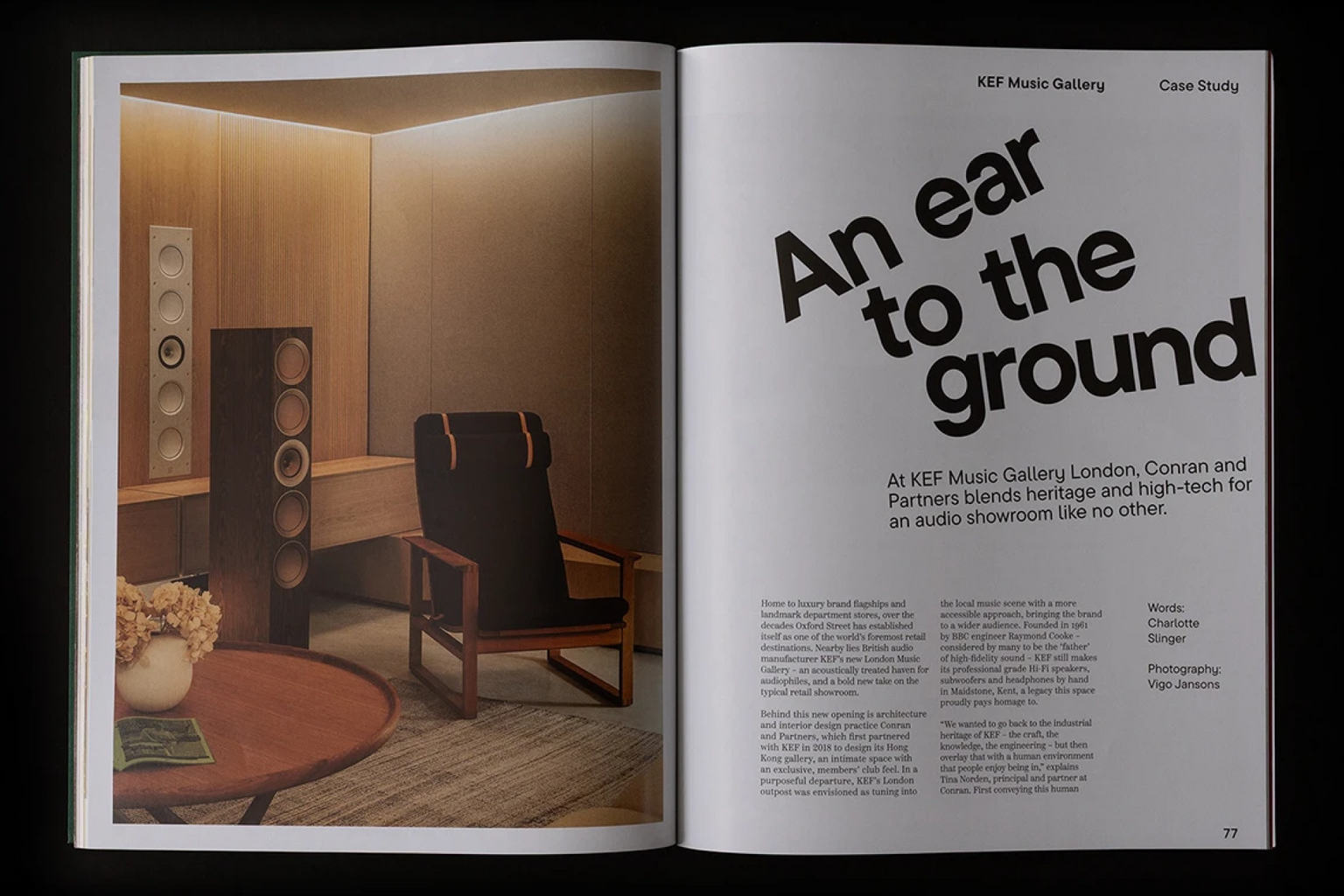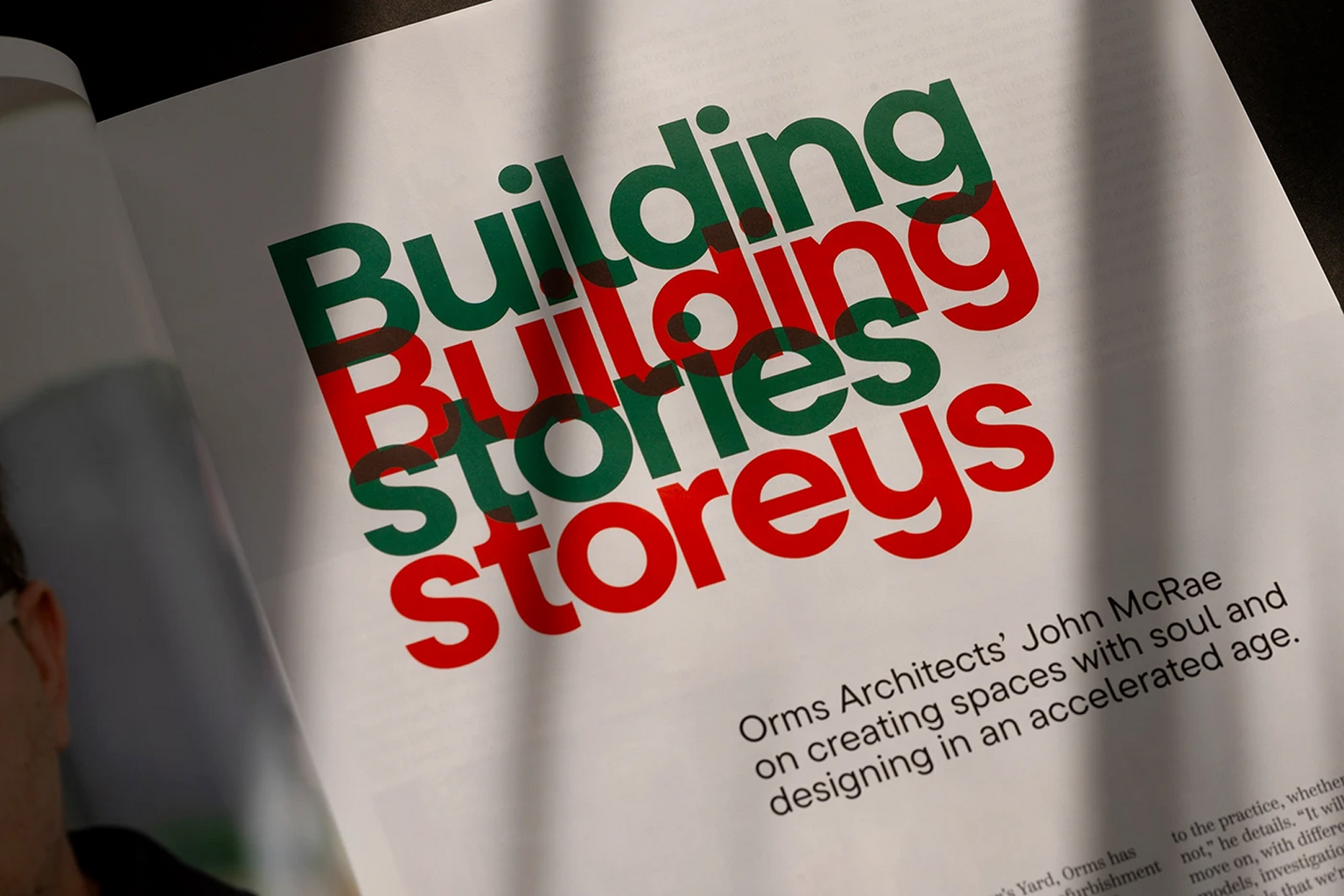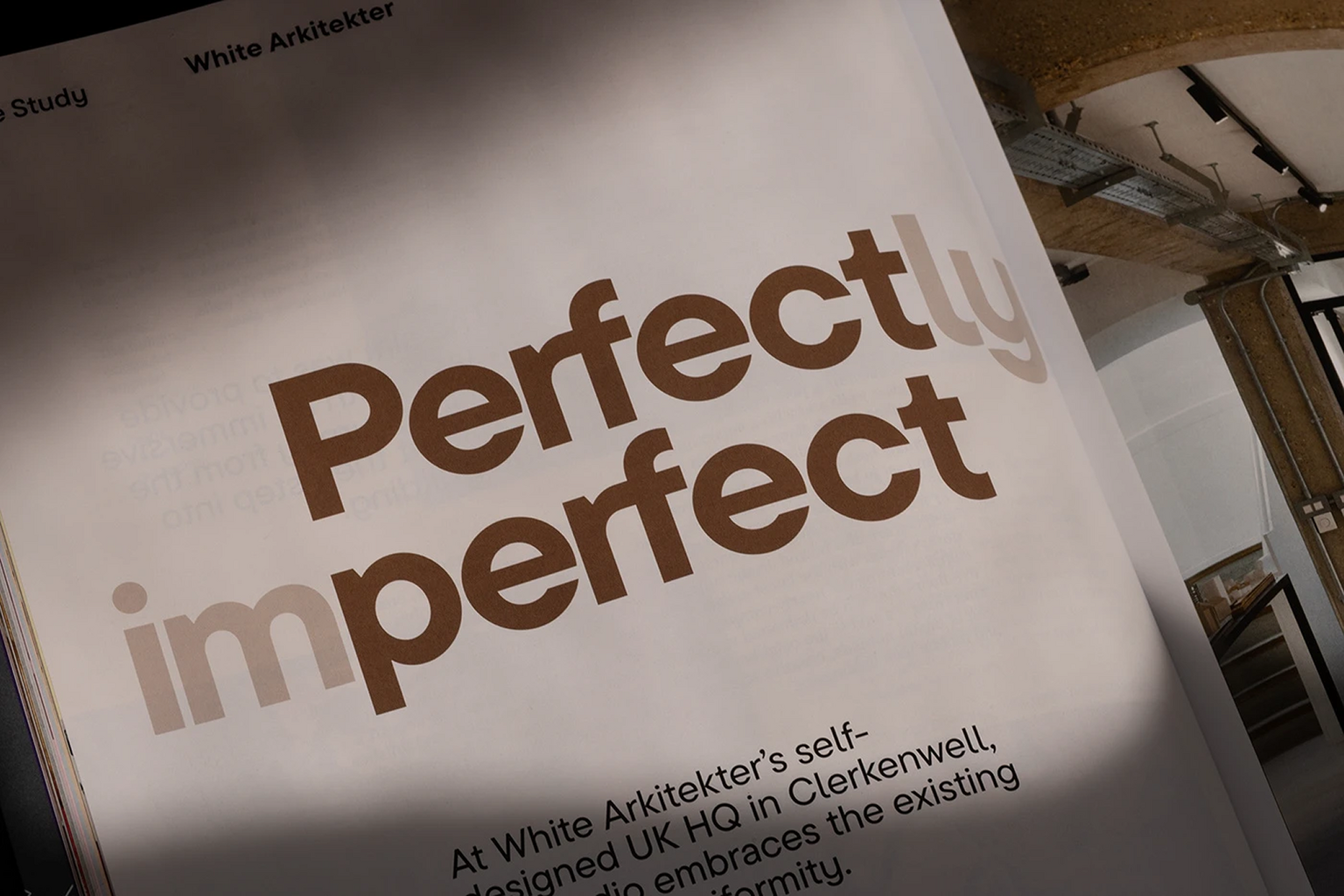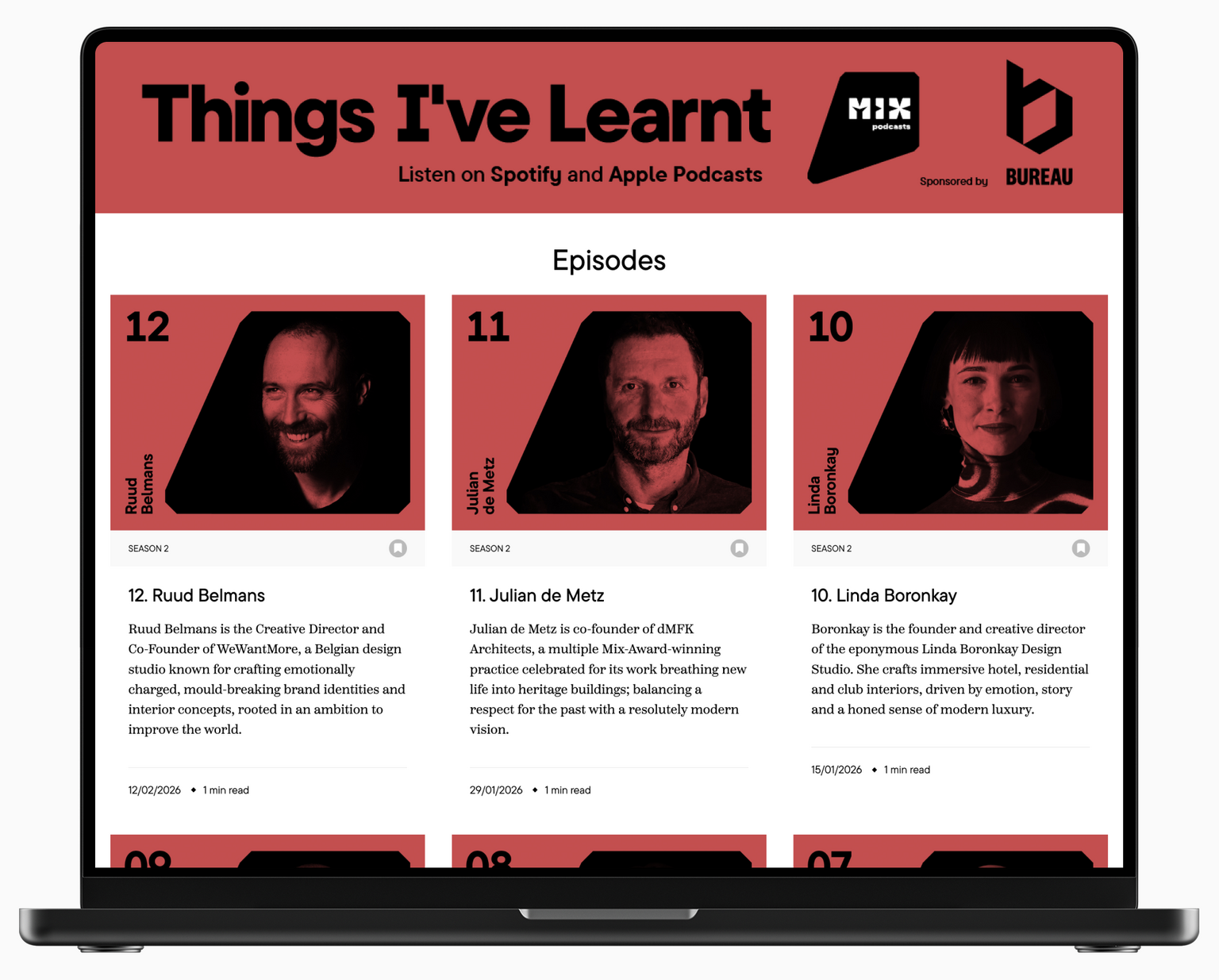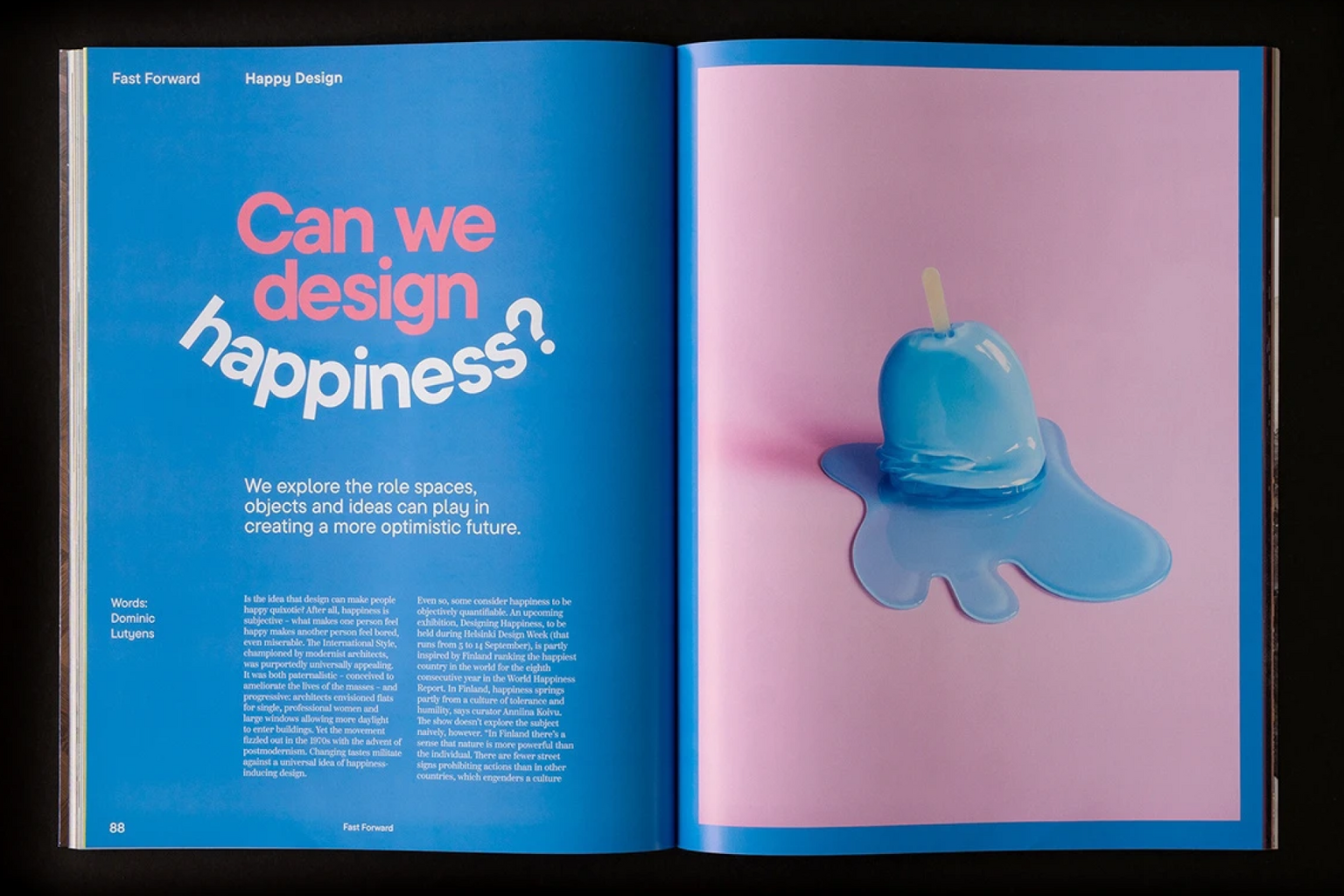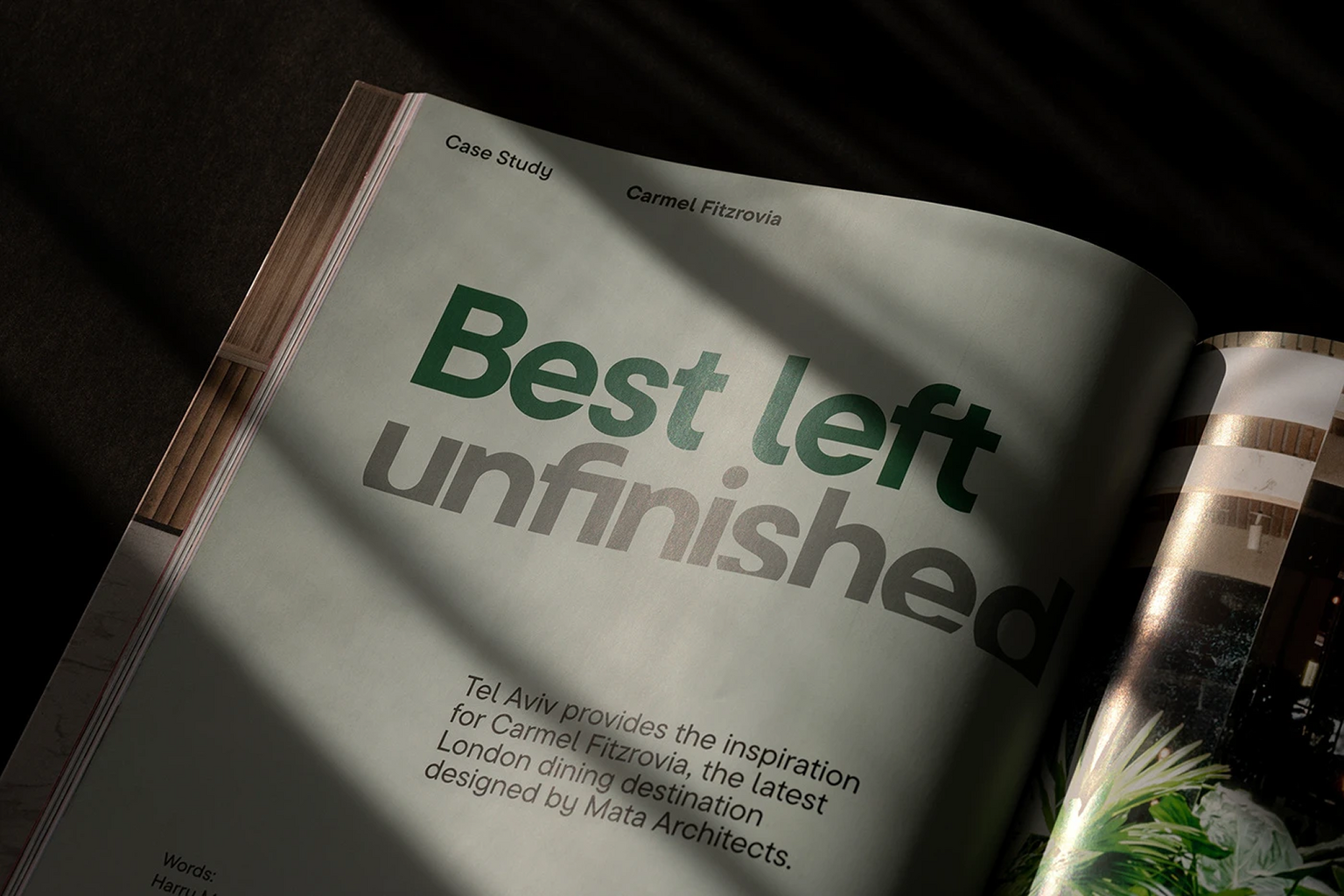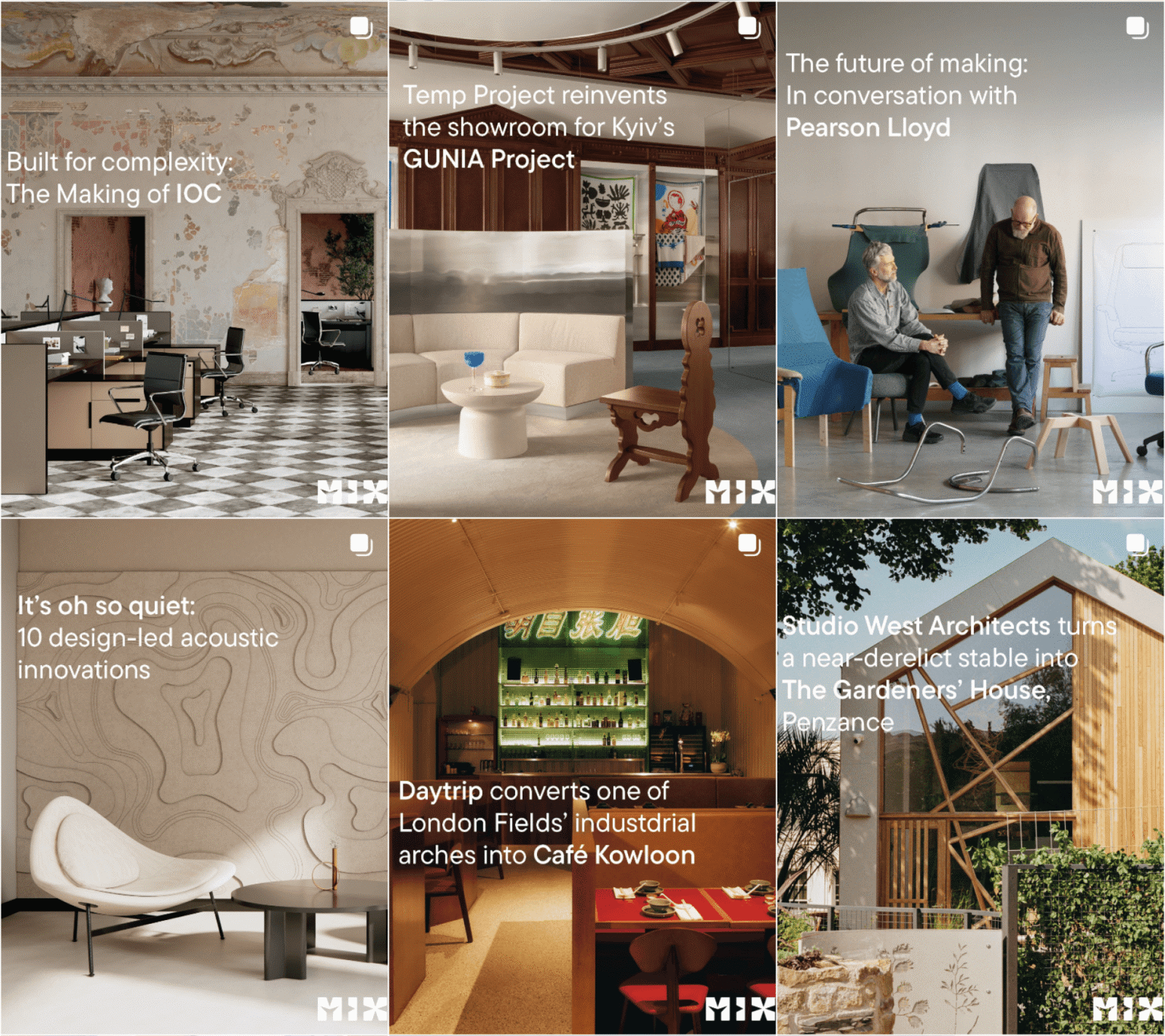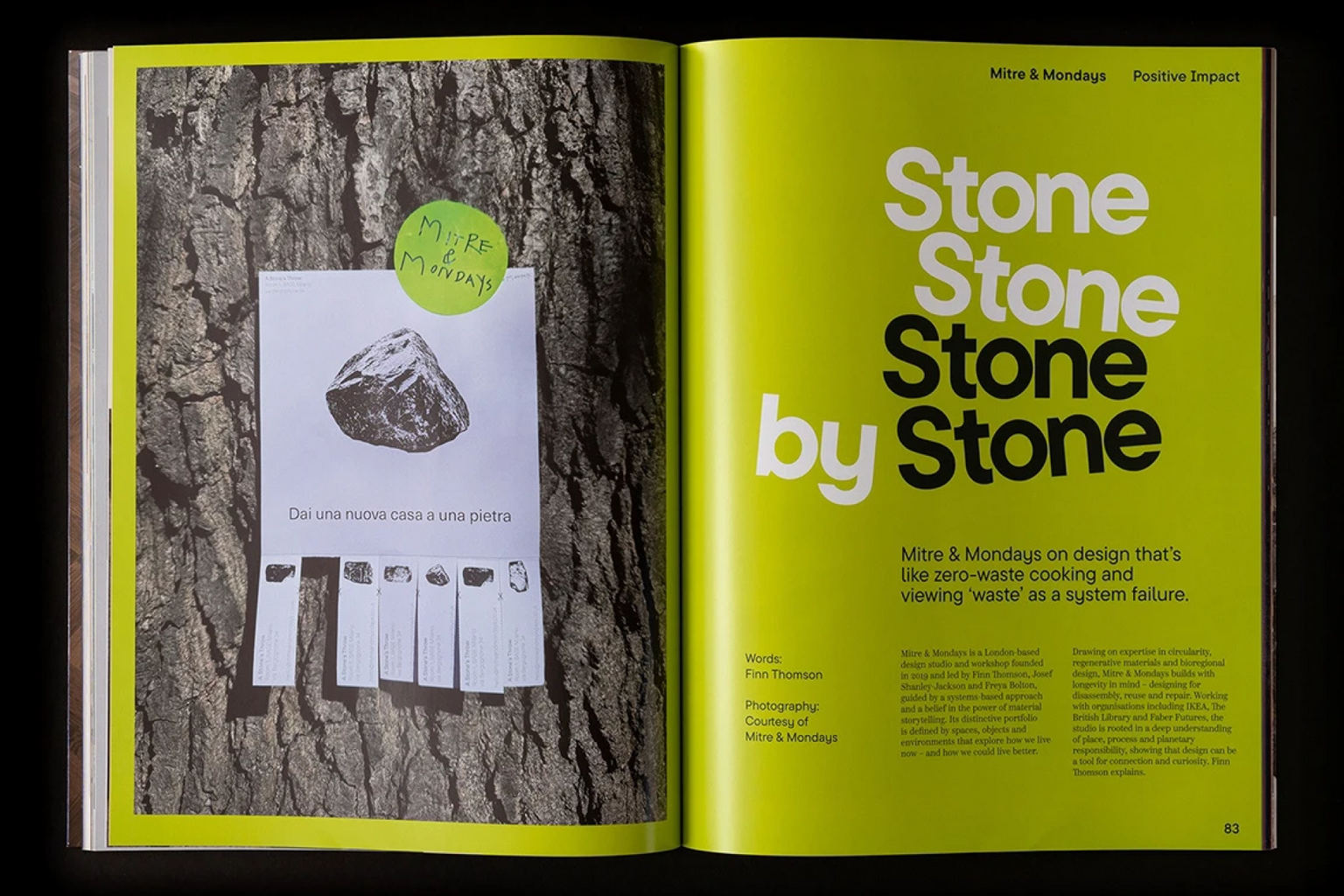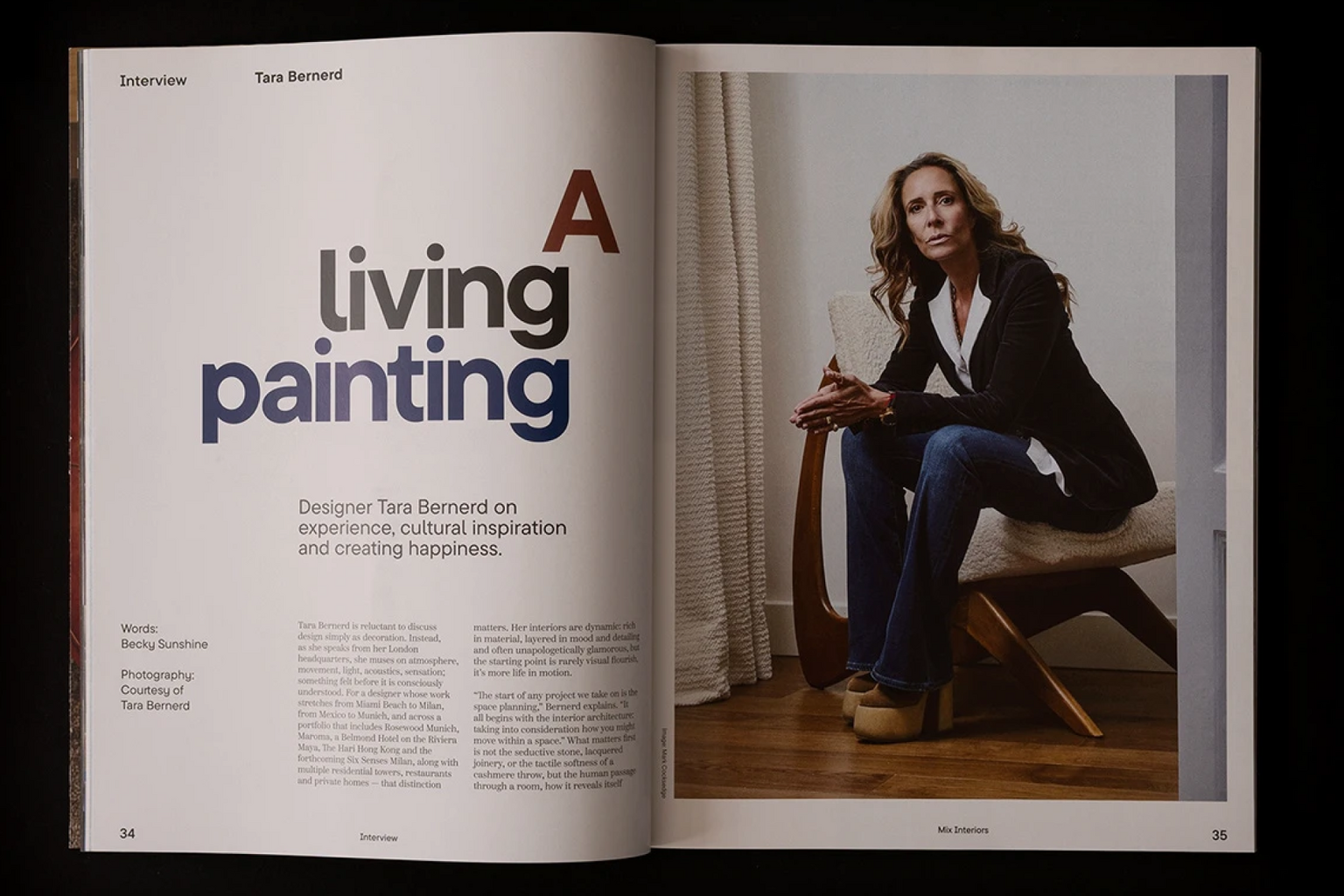
TT Commons™ Pro — фирменный шрифт компании Mix Interiors.
Mix Interiors — британское отраслевое медиа о коммерческом дизайне интерьеров и архитектуре. Компания выпускает журналы, публикует материалы о проектах, продуктах, трендах и специалистах индустрии, а также проводит профессиональные мероприятия и премии. Универсальный TT Commons™ Pro подчеркнул эстетичный и современный дизайн, при этом сохранив его лаконичность.